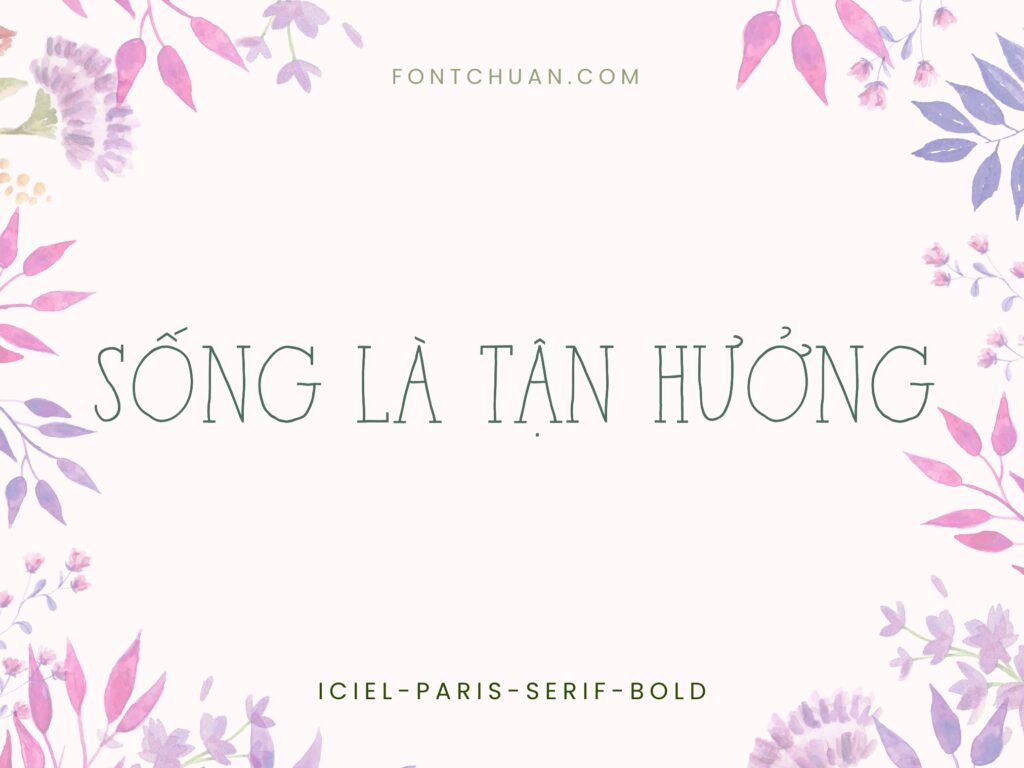
Font iCiel Paris Serif Bold Việt Hóa
Paris Serif là một kiểu chữ serif viết tay được thiết kế tại Paris, mang đậm phong cách nghệ thuật Art Deco. Font này bao gồm các ký tự viết hoa và viết thường, cùng với các dấu câu và số, hỗ trợ đa ngôn ngữ và được trang trí với các yếu tố nghệ thuật đặc trưng. Đặc biệt, Paris Serif đã được Việt hóa bởi iCiel, hỗ trợ tiếng Việt cùng nhiều ngôn ngữ khác, đáp ứng nhu cầu đa dạng của người dùng. Thành viên của Font Chuẩn đã sưu tầm và chia sẻ font này, giúp cộng đồng thiết kế ứng dụng dễ dàng trong các dự án của mình.
Về đặc điểm thiết kế, Paris Serif sở hữu các đường nét thanh mảnh, tinh tế, mang lại cảm giác sang trọng và cổ điển. Font này phù hợp cho các thiết kế như logo, tiêu đề, poster, bao bì sản phẩm và các ấn phẩm truyền thông cần sự thanh lịch và nghệ thuật. Ngoài ra, Paris Serif còn thích hợp cho các ngành nghề như quảng cáo, thiệp cưới, công nghệ và giáo dục, cùng các sự kiện đặc biệt như lễ hội, sinh nhật, Valentine và Trung thu.